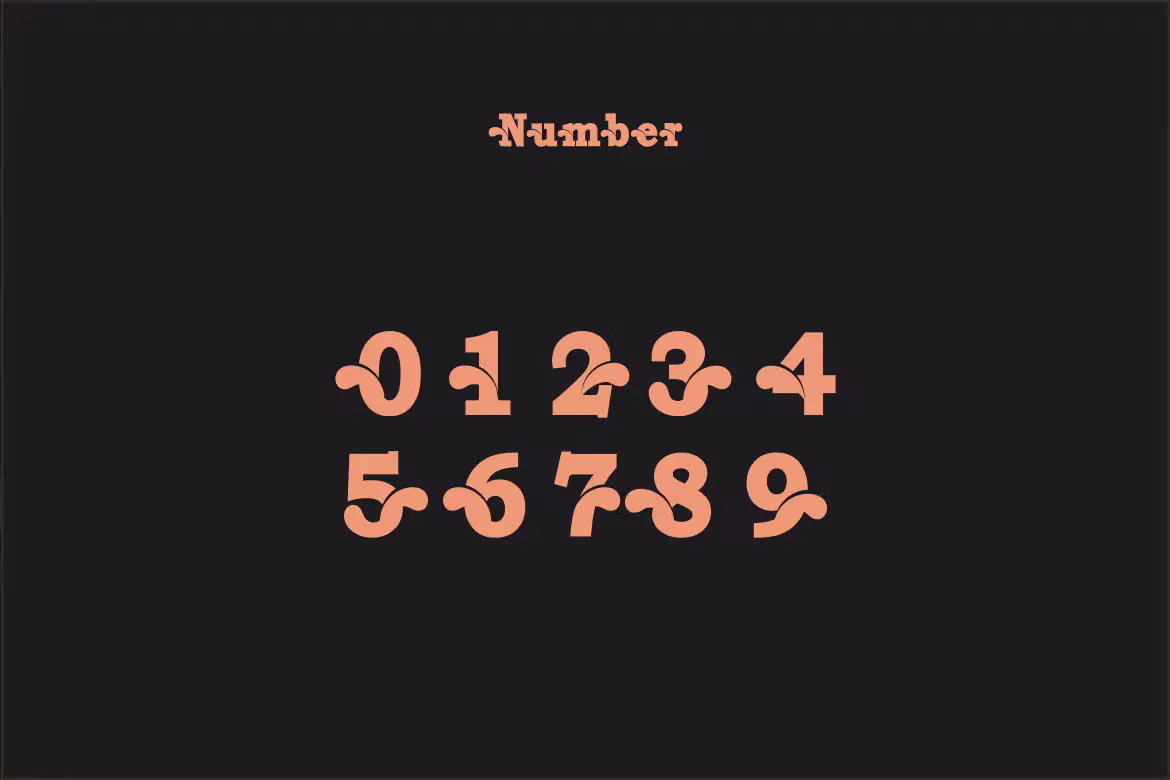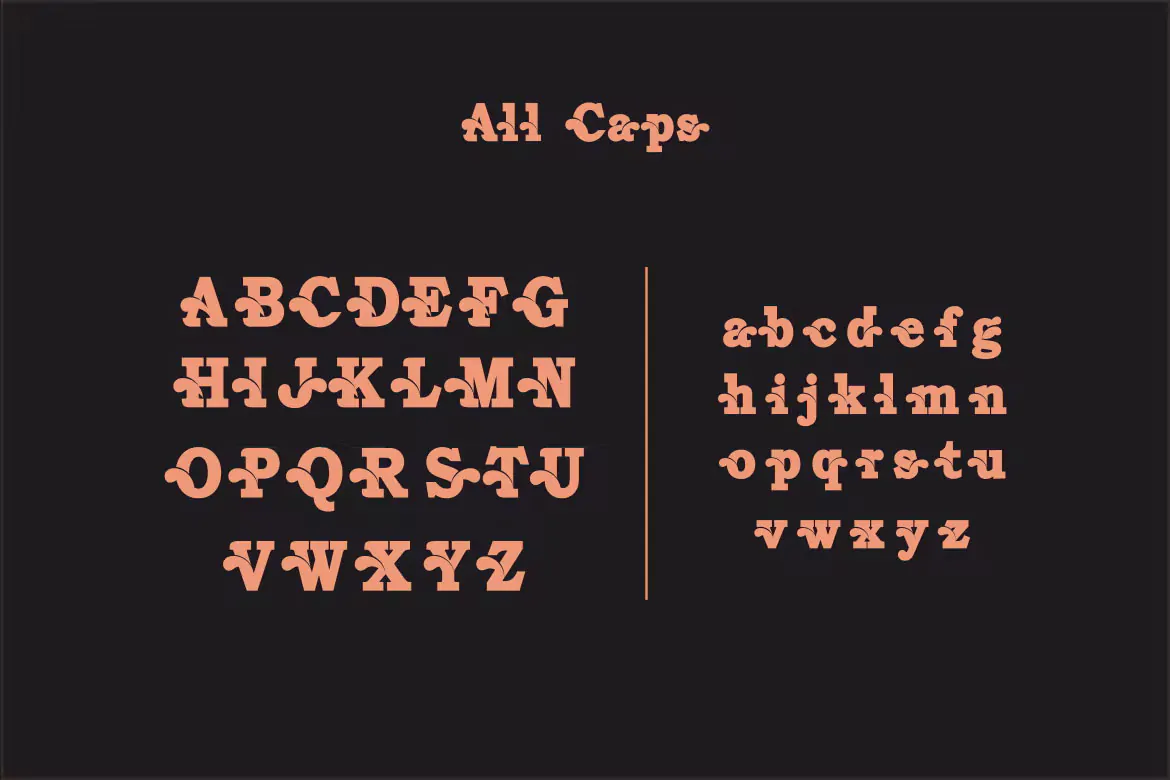
لوگو فونت Nubilka
لوگو فونت Nubilka یک سریف فونت انگلیسی طرح دار است که مناسب برای استفاده در طرح و پروژههای گرافیکی مختلف همچون طراحی پوستر، لوگو، برندینگ، بسته بندی و … میباشد.